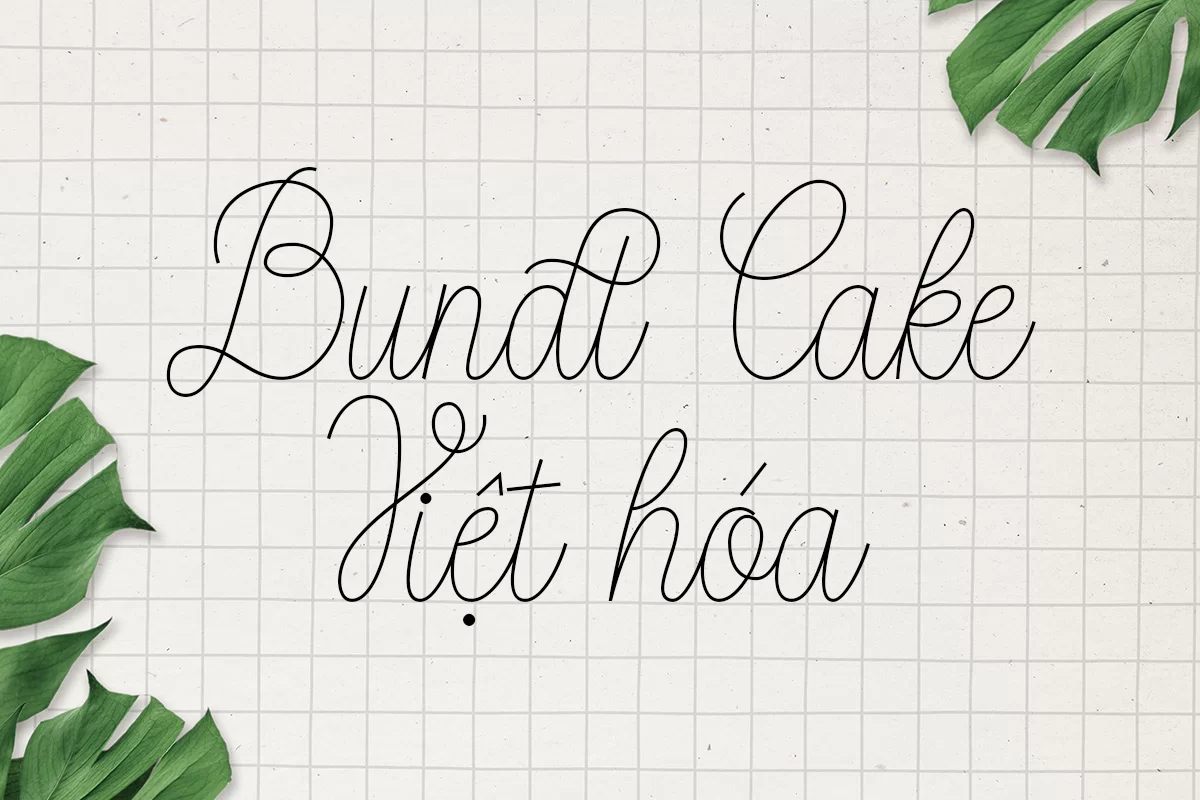
Bundt Cake Việt hóa là một font chữ viết tay (script) mang phong cách thanh mảnh, mềm mại và uyển chuyển. Các đường nét mảnh mai, uốn lượn tự nhiên giúp font này trở nên lý tưởng cho những thiết kế cần sự nữ tính, tinh tế và sang trọng.
Font phù hợp để sử dụng trong:
Với bộ ký tự đầy đủ tiếng Việt, Bundt Cake trở thành một lựa chọn tuyệt vời cho nhà thiết kế muốn kết hợp nét hiện đại và sự duyên dáng trong các dự án sáng tạo.
Font phù hợp để sử dụng trong:
- Thiệp mời, thiệp cưới, lời chúc.
- Logo thương hiệu, tiệm bánh, thời trang, mỹ phẩm.
- Các thiết kế typography, poster, social media.
Với bộ ký tự đầy đủ tiếng Việt, Bundt Cake trở thành một lựa chọn tuyệt vời cho nhà thiết kế muốn kết hợp nét hiện đại và sự duyên dáng trong các dự án sáng tạo.